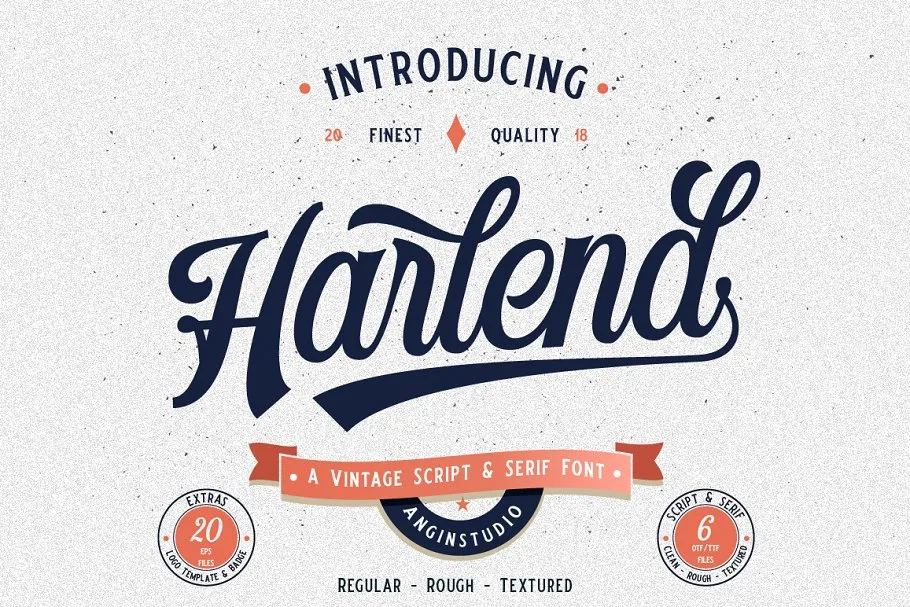
A Harlend Typeface é uma combinação única de tipo tipográfico vintage e serif que oferece um toque clássico para seu próximo projeto criativo. Ela foi inspirada na arte de pintura de sinal, rótulos e embalagens tradicionais dos Estados Unidos, com cada letra cuidadosamente elaborada para adicionar uma sensação de elegância aos designs vintage que você criará. Com alternativas inclusas no tipo, a Harlend é perfeita para aqueles que desejam manter seus projetos interessantes e originais, sem precisar se repetir com as mesmas opções. Esta fonte atinge desde os logos até rótulos de embalagens, impressões de camisetas, e tudo mais entre suas possibilidades. Ideal tanto para designers profissionais quanto para amadores que buscam um toque sofisticado em seus trabalhos de design, a Harlend Typeface é uma escolha inteligente para aqueles procurando por um tipo vintage moderno. O designer 0001themes trouxe vida ao Harlend, preservando o estilo clássico sem perder a capacidade de se adaptar e se transformar em diferentes contextos. Escolha este tipo para adicionar um toque autêntico ao seu próximo projeto, seja ele uma marca registrada ou uma camiseta personalizada.